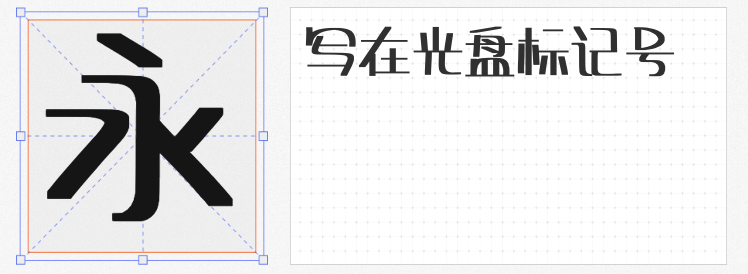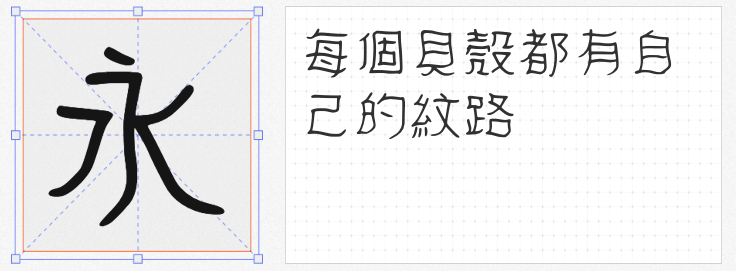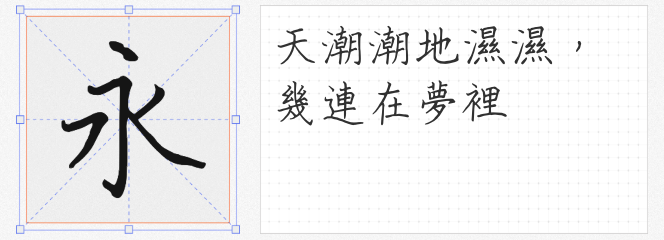
当寒风渐起、万物收藏,立冬节气为设计注入诗意与温度。如何在视觉呈现中传递节气氛围?选择契合主题的字体是关键。以下四款免费商用字体,以手写风格为基调,融合现代审美与趣味表达,为立冬主题设计注入鲜活生命力。
1. 清松手写体7
由设计师游清松打造的这款字体,以原子笔质感为基底,通过细腻的笔画转折与结构层次,赋予汉字流动的生命力。字形既有传统书法的韵律感,又融入几何化设计元素,笔画粗细对比自然,仿佛在纸上晕染出冬日的暖意。适用于节气海报标题或文化类宣传文案,既能传递立冬的静谧,又不失现代设计的轻盈感。
2. 随峰体 Beta
这款字体以逐字手写的啫喱笔痕迹为特色,刻意保留书写时的飞白与墨点,营造出未经修饰的质朴感。笔画边缘的微微晕染与不规则转折,恰似冬日窗棂上凝结的霜花,传递自然随性的氛围。适合用于手账插画、节气手写卡片或文艺类设计,让观者感受到手作的温度。
3. 文心喜乐体
以“喜乐”为名的字体自带治愈气质,饱满的笔画与错落有致的横竖对比,搭配高光纹理的肌理效果,仿佛阳光穿透云层洒在雪地上。字形结构松紧有度,既适合作为标题吸引目光,也能用于正文段落保持阅读舒适度。在立冬主题设计中,可搭配暖色调背景,传递围炉煮茶的温馨场景。
4. 宅在家麦克笔
这款字体以马克笔书写为灵感,中宫舒展的笔画结构与夸张的收笔弧度,形成俏皮活泼的视觉节奏。粗细均匀的笔画搭配圆润转角,如同孩童在雪地上留下的脚印,充满天真意趣。适合用于社交媒体图文、节气活动海报或儿童类设计,为立冬增添一抹灵动色彩。
四款字体各具特色,从传统书法的雅致到现代手写的趣味,覆盖多元设计场景。更难得的是,它们均支持免费商用,让创意无拘无束。这个立冬,不妨用文字的温度,勾勒季节的轮廓。